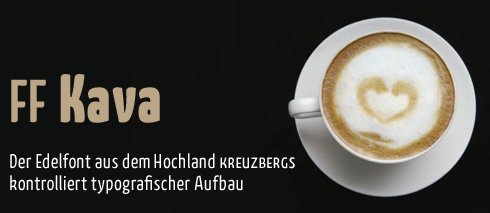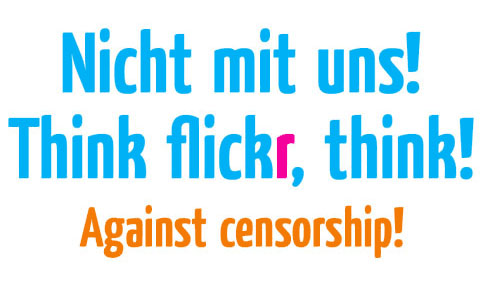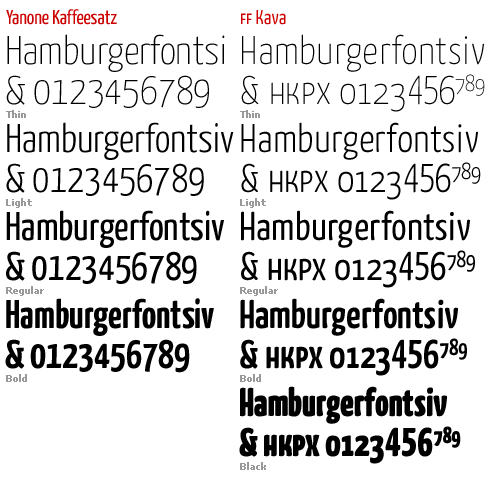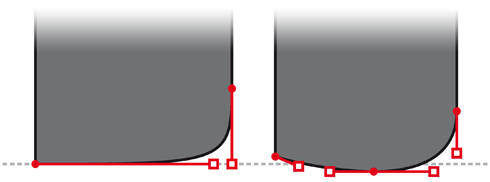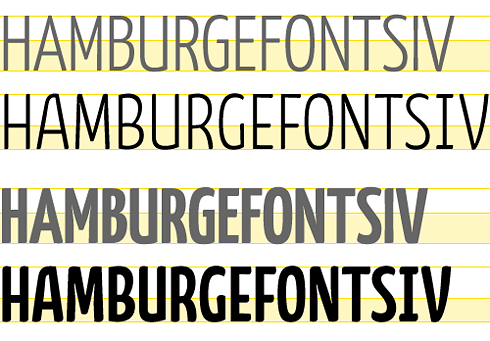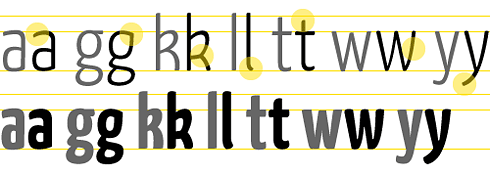
FF Kava – die neue, professionelle OpenType-Schriftfamilie von Yanone – ist der dritte FontFont-Neuentwurf in unserer kleinen Serie zum jüngsten FontFont-Release Nº 49 (siehe auch Wie die FF Unit-Slab-Schriftfamilie entstand und FF Duper – ›Mein Buchstabenkarussell dreht größere Runden‹). Yanone, 1982 in Dresden als Jan Gerner geboren, ist wahrlich kein Unbekannter in der Schriftszene, und das hat auch mit Kava zu tun, denn die Kava-Familie ist die Weiterentwicklung seines Free-Fonts Kaffeesatz, der weltweit im Einsatz ist.
Yanone lebt heute unweit von Weimar, wo er als Designer und Schriftentwerfer, Multimedia-Künstler, Discjockey und Sound-System-Operator tätig ist. Nachdem er 9 Jahre seiner Kindheit in Addis Abeba, der Hauptstadt Äthiopiens verbracht hat, kehrte er 1997 in das wiedervereinigte Deutschland zurück, wo er die Schule abschloss. Im Alter von 14 Jahren setzte ihn sein Vater zum ersten Mal vor einen Computer, um ihm die Programmiersprache Pascal beizubringen. Das weckte sein Interesse an der Informationswissenschaft. Die Gestaltung eines Jahrbuch anlässlich seines Abiturs 2000, brachte ihn erstmals mit Grafikdesign in Berührung. 2002 begann Yanone sein Studium an der Bauhaus Universität in Weimar, das er vor einem Jahr in Amman (Jordanien) abschloss. Zuvor absolvierte er ein Praktikum bei FSI FontShop international, Herausgeber der FontFont-Schriftbibliothek.
In Amman arbeitete Yanone eng mit Ahmad Humeid zusammen, Sprecher auf der TYPO Berlin 2001 Brands und Geschäftsführter des Designbüros Syntax. Das war gerade mit der Entwicklung eines neuen Corporate Designs für die jordanische Hauptstadt beschäftigt. Jan brachte sein Font-Know-how mit ein und entwickelte für das CI von Amman eine Schriftfamilie mit 22 Fonts: arabische plus lateinische Schriftzeichen, gerade und kursiv, Sans und Serif. Zum ersten Mal wagte sich ein Schriftentwerfer an eine kursive arabische Schreibschrift. Die Familie wird 2010 in der FontFont-Bibliothek unter dem Name FF Amman erscheinen.
Kaffeesatz im Packaging-Einsatz: auf dem Kürbiskernöl in der Steiermark und den Laugenbrezeln von Ditsch
Kaffeesatz im Plakat-Einsatz: in Frankreich, Deutschland und Neuseeland (McDonald’s)
FF Kava kam 2004 als Yanone Kaffeesatz zur Welt. Es war Yanones erste zu Ende entwickelte Schrift, denn er war noch ein Fontlab-Anfänger. Der fette Schnitt war eine Reminiszenz an die Kaffeehaus- und Kaffeemarkentypografie der 20er Jahre, während der sehr leichte Schnitt die Brücke zur Neuzeit schlug. Weil er unsicher war und noch wenig Erfahrung mit der Font-Szene hatte, entschloss sich Yanone, die Schrift als Free-font in die Welt zu setzen. Schon bald stellte sich dies als die beste Idee heraus, denn binnen weniger Monate verbreitete sich der Font tausendfach und bescherte Jan internationales Interesse. Allein von seiner eigenen Webseite wurde der Fonts über 100.000 mal geladen. Er ist auf der ganzen Welt zu entdecken, von den Malls von Dubai bis zur McDonald’s-Straßenwerbung in Neuseeland.
Zur Bekanntheit der Schrift trugen auch Zehntausende Flickr-User bei die protestierten, als der Bilderdienst vor zwei Jahren in Europa eine Zensur einführte (Fontblog berichtete: Flickr-User gehen auf die Barrikaden). Sie drückten ihren Unmut mit der oben abgebildeten Hinweistafel aus – gesetzt aus Kaffeesatz, die entweder als Profilbild verwendet wurde oder als dauerhafter letzter Upload.
Die neue FF Kava ist eine komplette Überarbeitung und Erweiterung des Free-Font-Klassikers. Der auffälligste Unterschied ist der Black-Schnitt, den Yanone schon zu Kaffeesatz-Zeiten gerne gemacht hätte. Weniger auffällig ist der Ausbau zur professionellen OpenType-Familie, mit umfassender Sprachunterstützung, integrierten Kapitälchen, diversen Ziffernsätzen und allem Zauber, den man von OpenType-FontFonts gewohnt ist.
Darüber hinaus bügelte Yanone 5 Jahre nach Kaffeesatz viele Ungereimtheiten glatt, über die er sich damals gar nicht bewusst war. Erst dadurch passierte FF Kava die strengen Augen des FontFont-Typeboards und durfte sich nun Auge in die Riege von Klassikern einreihen, zu der auch FF Dax gehört, eine Schrift, die Kaffeesatz sicherlich beeinflusst hat. FF Kava ist jetzt ein professionelles Werkzeug, was Kaffeesatz nie war – außer in der weltweiten Verbreitung.
Für die Experten unter den Fontblog-Lesern sei noch auf einige Änderungen im Detail hingewiesen, die den Charakter der Schrift – im Großen – in ein neues Licht rücken.
Obwohl die Strichenden der Kaffeesatz (links) an einer Ecke gerundet waren, stehen die Buchstaben auf flachem Fuß. Kennzeichnend für die neue FF Kava (rechts) sind gewichtete, bogenförmige Strichenden, die der Schrift einen lässigeren Auftritt verleihen. Ein weiteres Detail, unsichtbar für Laien aber gravierend für das Schriftbild der FF Kava, ist die Ausführung der Kurven. Yanone gibt heute zu, dass er 2004 als Autodidakt keinen »blassen Schimmer« davon hatte, wie man ordentliche Bézier-Kurven zeichnet. Ergebnis: Die Strichenden der Kaffeessatz-Buchstaben sind im Ungleichgewicht, die Grundlinie »tanzt«. FF Kava hat korrigierte Strichenden, mit Überhang und gleich gewichteten Ecken.
Ein anderes Problem bei Kaffeesatz waren die Versalien, denen zu wenig Aufmerksamkeit geschenkt wurde. Die einzelnen Buchstaben an dieser Stelle zu vergleichen würde hier zu weit führen. Yanone beschreibt es so: »Die Großbuchstaben waren nicht harmonisch komponiert und bestimmte Formprinzipien hab ich nicht eingehalten. Schließlich baute ich das gesamte Versalalphabet von Grund auf neu, mit ordentlichen Proportionen, einheitlichen Innenräumen, Ink-traps und vielen Verfeinerungen.« Dabei entdeckte er sein Faible für Buchstaben mit niedriger Taille, ein Stilmittel, dass er auf alle Versalien anwendete.
Bei den Kleinbuchstaben der FF Kava (schwarz) änderte Yanone unzählige Details. Einige dienen der besseren Lesbarkeit – wie zum Beispiel beim l –, andere überarbeitete er aus ästhetischen Gründen, zum Beispiel k, g und y.